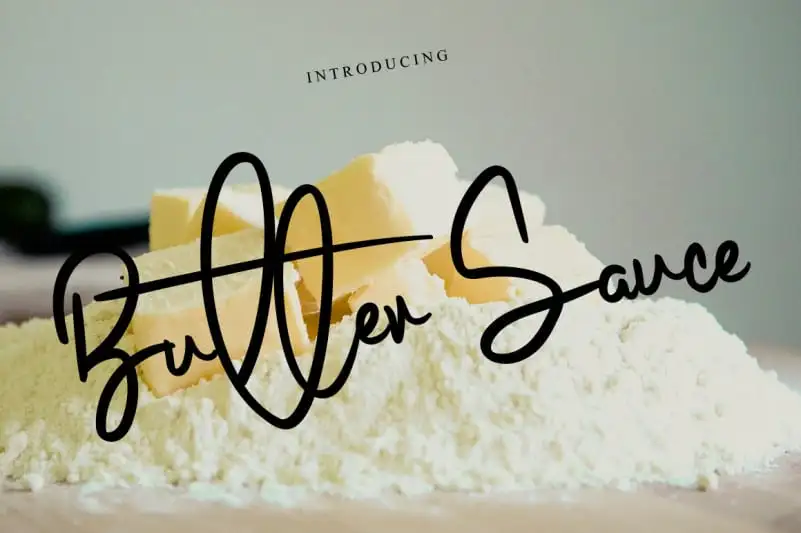
Butter Sauce Script Font – Fonte Grátis
Butter Sauce Script Font
A Butter Sauce Script Font é uma elegante fonte cursiva escrita a mão, leve e delicada. Suave e graciosa, esta fonte será um toque perfeito para sua próxima ideia de design. Ela trará ao seu projeto um toque descontraído e romântico que certamente deixará tudo mais atraente e divertido. Composta por letras curvas e arredondadas, ela é ideal para adicionar uma pitada de alegria aos teus trabalhos pessoais ou profissionais. A Butter Sauce Script Font será um complemento irresistível em qualquer projeto que você estiver desenvolvendo.